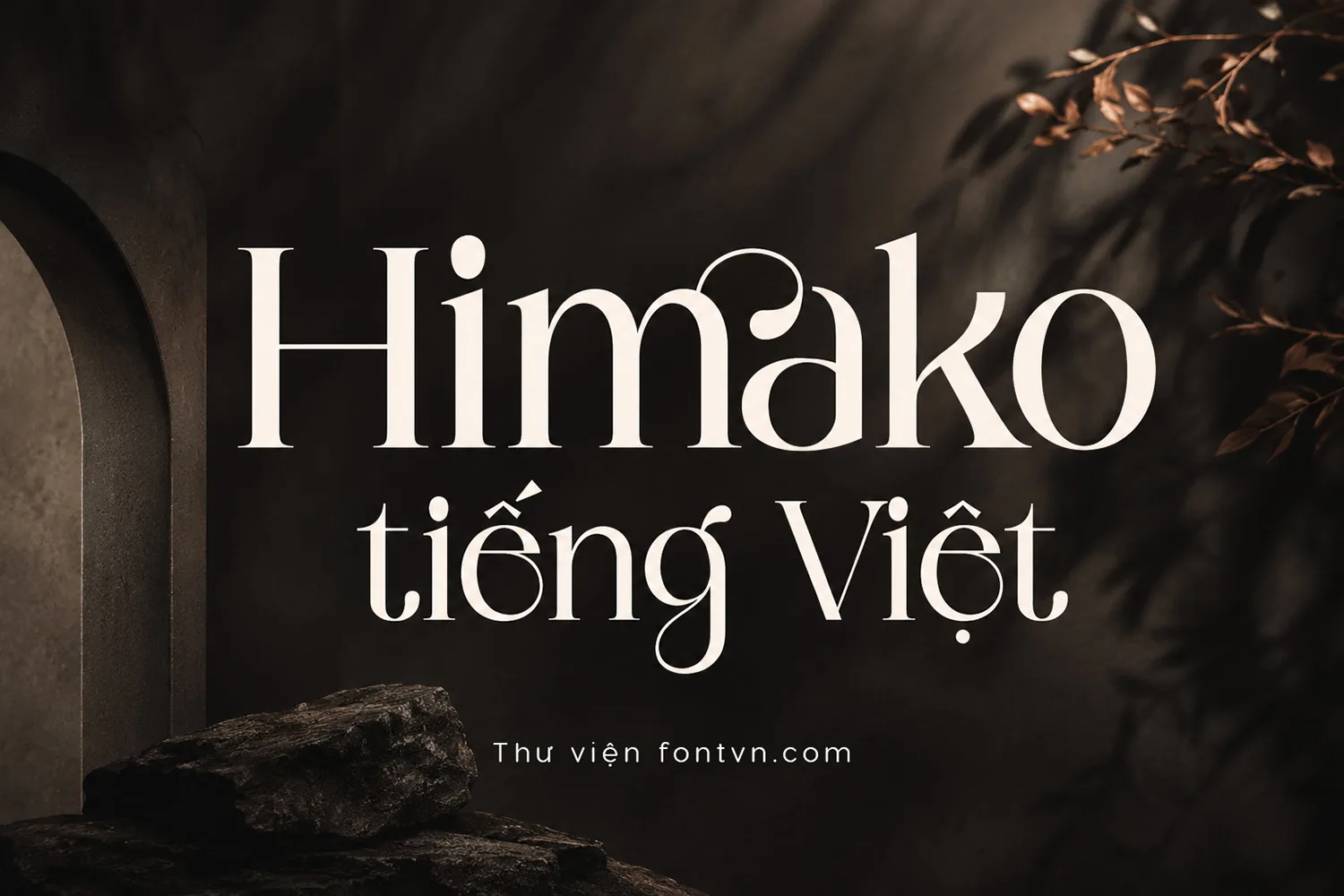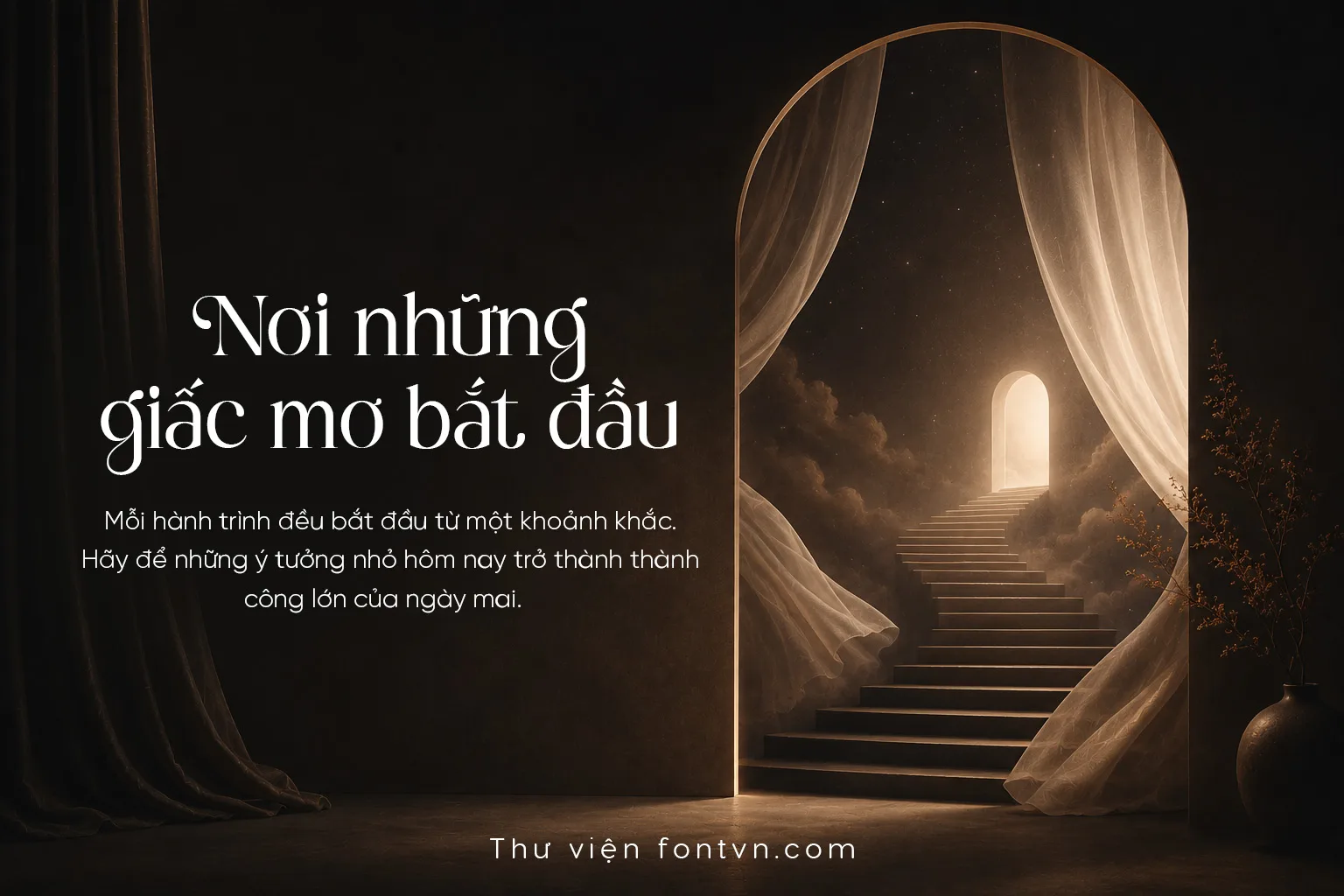
DVN Himako tiếng Việt – Font chữ thời trang và cao cấp
DVN Himako là kiểu chữ serif tương phản cao mang phong cách thanh lịch, thời trang và giàu tính nghệ thuật. Font nổi bật với những đường nét mảnh – dày rõ rệt, kết hợp các đường cong mềm mại và những chi tiết trang trí tinh tế, tạo nên cảm giác sang trọng nhưng vẫn có cá tính riêng.
Bên cạnh bộ ký tự tiêu chuẩn, DVN Himako còn được thiết kế với nhiều Alternate & Ligature độc đáo, giúp người dùng dễ dàng biến đổi hình dáng chữ và tạo ra những bố cục typography ấn tượng.
Font đặc biệt phù hợp cho thời trang, mỹ phẩm, nước hoa, thương hiệu cao cấp, wedding, editorial, logo, packaging, poster và các dự án mang phong cách luxury.